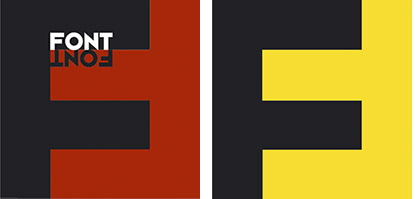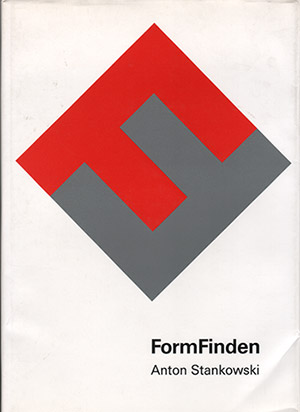
Formen finden und nicht stehlenThema Nummer 1 der internationalen Corporate-Design-Szene: Das neue Logo
des Software-Herstellers Quark soll eine Kopie sein. Nach einem
Schlüsselerlebnis 1995 bin ich vorsichtig geworden mit
Plagiatvorwürfen. Die Wahrscheinlichkeit, dass Menschen eine simple,
zwingende Form unabhängig voneinander entwickeln ist ziemlich hoch. Weiterlesen ...
![]() Es wird in aller Breite und Tiefe hergezogen über das neue
Quark-Firmenzeichen, zum Beispiel bei Macworld UK, bei Antipixel, NewsDesigner.com und bei adland. So
sehen die beiden Werke nebeneinander gestellt
aus:
![]() Das Logo des Schottischen Kunstverbandes (oben) stellt wahrscheinlich ein kleines a dar, bei Quark handelt es sich um ein Versal-Q. In beiden Fällen wurden die Buchstaben simplifiziert: auf die geometrische Grundformen des Kreises mit weißem Innenraum und einer Quadratecke unten rechts. So was kann vorkommen, behaupte ich, seitdem mir dieses Buch 1995 in einem Antiquariat begegnete: ![]() Anton Stankowski: FormFinden; 190 Seiten, 84 farbige Abbildungen, Gerd Hatje, Stuttgart, 1991 (Foto: Fontblog) Anton Stankowski (1909 – 1998) war ein deutscher Grafiker, Maler und Fotograf. Berühmt wurde er durch seine Gestaltungslehre, die er Anfang der 30er Jahre in der Schweiz entwickelte. 1951 gründete er in Stuttgart sein eigenes grafisches Atelier, wo er unter anderem die Wortmarken für Iduna und Viessmann entwarf. In den 70er Jahren entwickelte er zusammen mit Karl Duschek die Firmenzeichen für die Deutsche Bank, die Münchener Rück Versicherung, REWE und den Olympischen Kongress Baden-Baden. Dass Menschen am Ende eines unabhängig voneinander entwickelten Gestaltungsprozesses zu gleichen Formen kommen habe ich nicht in Stankowskis Buch »FormFinden« erfahren, sondern – mit Schrecken – direkt auf dem Schutzumschlag. Ihn ziert die quadratische Form zweier ineinander greifender Fs, eine Versinnbildlichung des Buchtitels »FormFinden«. Dasselbe Zeichen war und ist seit 1991 das Logo der FontFont-Schriften-Bibliothek, für deren Entwicklung ich seit dieser Zeit mit verantwortlich bin. Hier das FontFont-Logo in seiner Originalfassung und der seit 1994 gebräuchlichen Ausführung: ![]() Original FontFont-Logo (1990) und die seit 1994 gültige gelb-schwarze Fassung Anders als bei den Quark/Scottish-Arts-Council-Logos kann man hier nicht mehr nur von einer sehr großen Ähnlichkeit sprechen: die Stankowski- und die FontFont-Form sind absolut identisch. Sie sind es, weil die Art der Verschmelzung zweier verschiedenfarbiger Fs mit konstanter Strichstärke keine andere Lösung zulässt. Interessant ist, dass sie fast zur gleichen Zeit entstanden sind. Ich versichere für meinen Teil und die FontFont-Herausgeber: Das FontFont-Zeichen ist ohne Kenntnis des Stankowski-Buch-Titels entstanden. Zu genau erinnere ich mich an den mehrere Tage dauernden Entwicklungsprozess, beginnend mit zwei nebeneinander stehenden Fs, die in vielfältiger Weise zueinander gestellt wurden: Rücken an Rücken, punktsymmetrisch, achsensymmetrisch und zig Zwischenlösungen. Am Ende ergab sich die einzige mögliche Idealform ... so wie sie auf dem Stankowski-Buch zu betrachten ist. Ich könnte die Gegenfrage stellen: Kannte der Gestalter des Buchumschlags möglicherweise das FontFont-Zeichen? Es würde mich wundern, weil es zu der Zeit frisch war und noch nicht weit verbreitet. Nein, ich stehe zu der These: simple, zwingende Formen können zur gleichen Zeit an unterschiedlichen Orten unabhängig voneinander identisch entstehen. PS: Auch interesseant ... eine Google-Suche förderte eben eine Cover-Variante des Stankowski-Buches hervor, die mir bis dato nicht bekannt war ... ![]() Herausgegeben: Di - September 20, 2005 at 12:39 vorm. | |